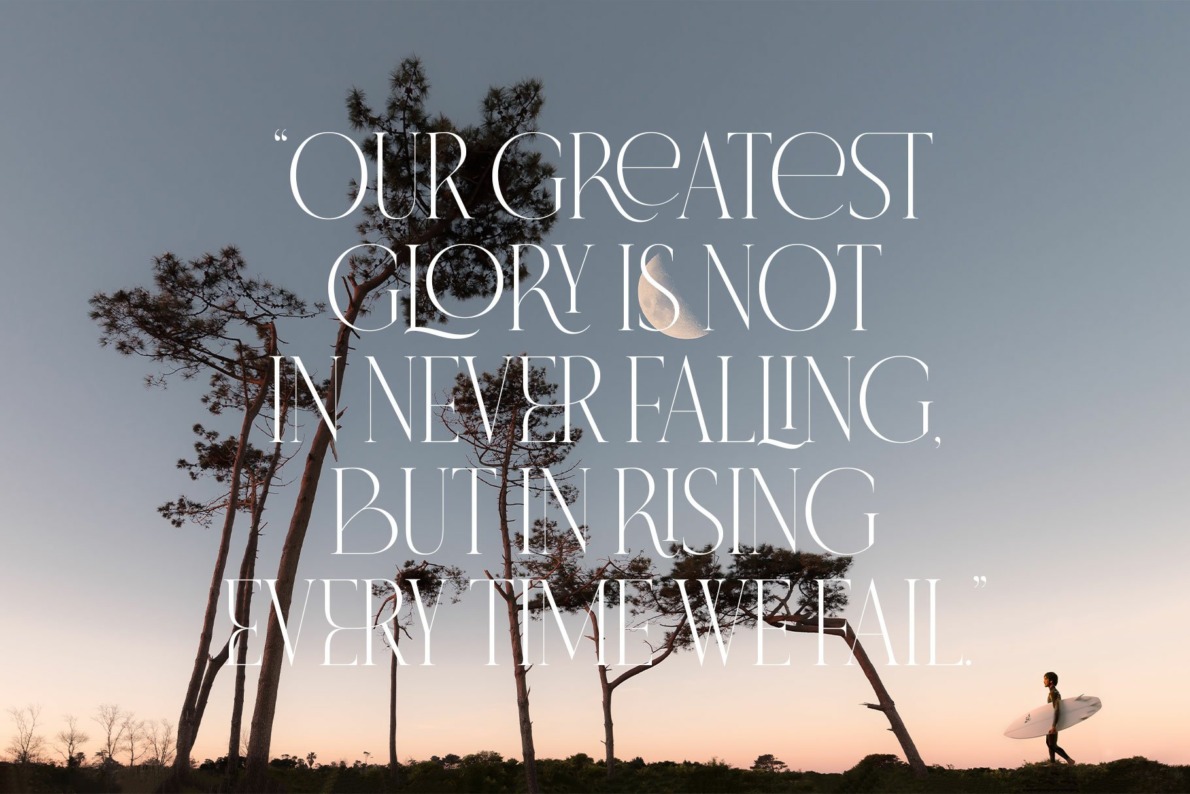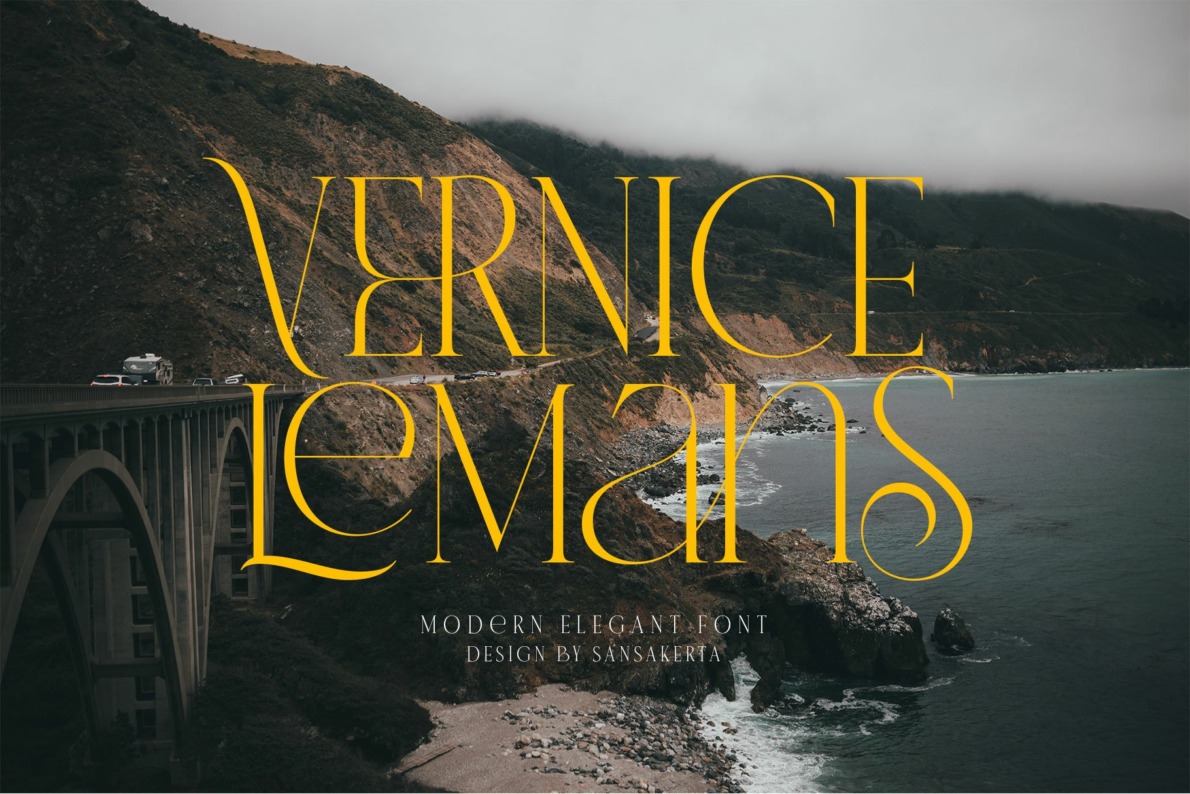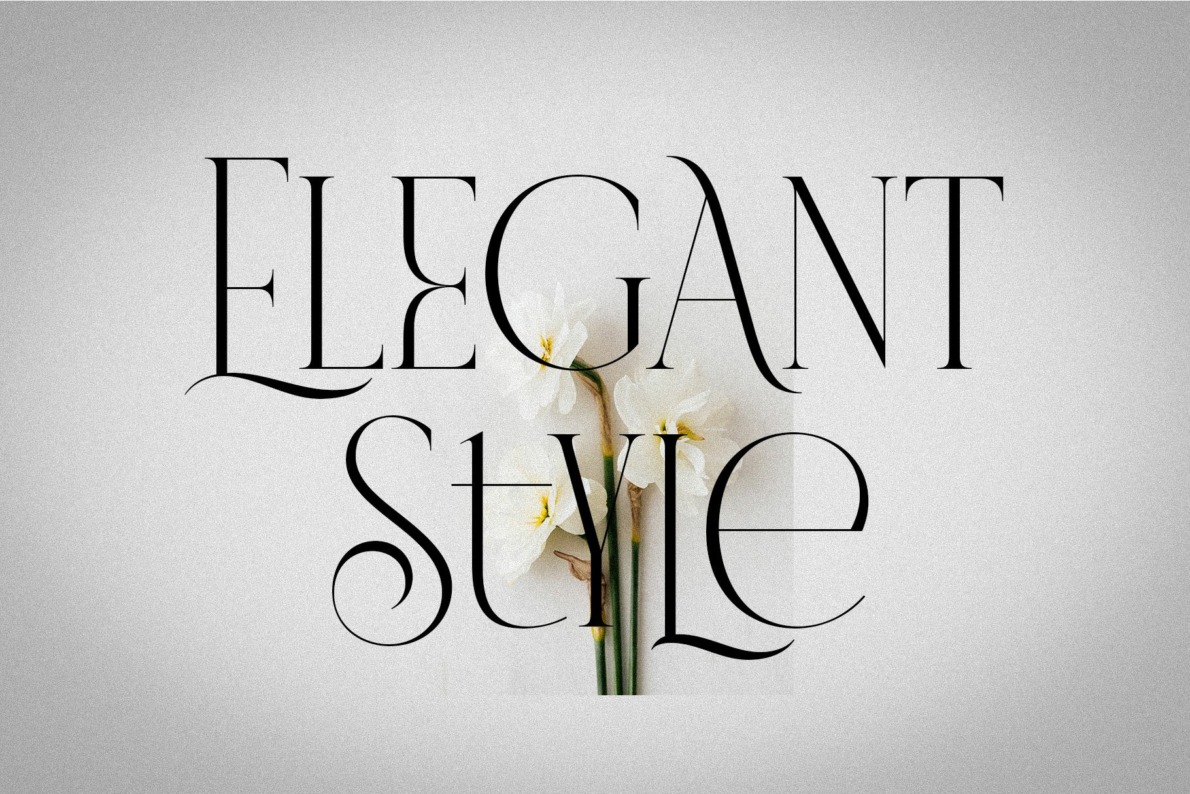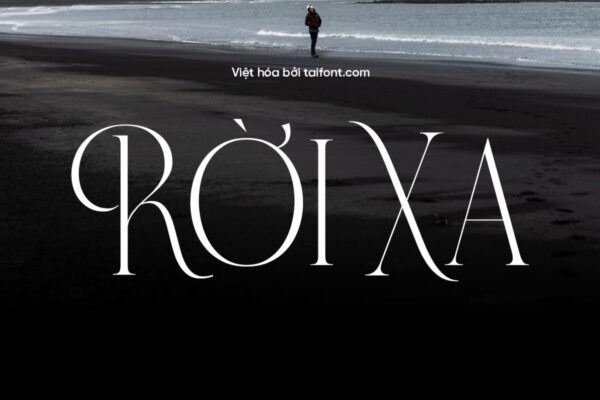
Giới thiệu về Font TF Vernice Lemans Việt hóa
TF Vernice Lemans Việt hóa là một font chữ có chân (serif) nổi bật với vẻ đẹp tinh tế, sang trọng và đầy cuốn hút. Font này được thiết kế với sự tỉ mỉ, kết hợp giữa nét cổ điển và một chút nét hiện đại, tạo nên phong thái đẳng cấp và sự thanh lịch vượt thời gian.
Với tính thẩm mỹ cao, Vernice Lemans là lựa chọn lý tưởng cho các thiết kế đòi hỏi sự chuyên nghiệp và sự thu hút, đặc biệt là trong các lĩnh vực:
- Thiết kế thời trang: Hoàn hảo cho các thương hiệu thời trang cao cấp, nhãn mác sản phẩm, lookbook, hoặc các ấn phẩm quảng bá bộ sưu tập. Font này giúp truyền tải sự tinh tế, phong cách và đẳng cấp của trang phục.
- Mỹ phẩm: Lý tưởng để sử dụng trên bao bì sản phẩm, catalogue, hoặc các chiến dịch marketing, giúp khẳng định chất lượng và sự sang trọng của thương hiệu mỹ phẩm. Vernice Lemans sẽ làm nổi bật vẻ đẹp của sản phẩm, thu hút ánh nhìn của khách hàng.
- Tạp chí: Phù hợp cho các tạp chí về thời trang, làm đẹp, nghệ thuật hoặc các ấn phẩm cao cấp khác. Font này giúp các tiêu đề, bài viết, hoặc các phần nội dung trở nên cuốn hút, chuyên nghiệp và dễ đọc, nâng tầm đẳng cấp của tạp chí.
Với TF Vernice Lemans Việt hóa, bạn có thể dễ dàng tạo ra những thiết kế không chỉ đẹp mắt mà còn truyền tải được thông điệp về sự tinh tế, sang trọng và đẳng cấp, góp phần nâng tầm giá trị cho dự án của bạn.